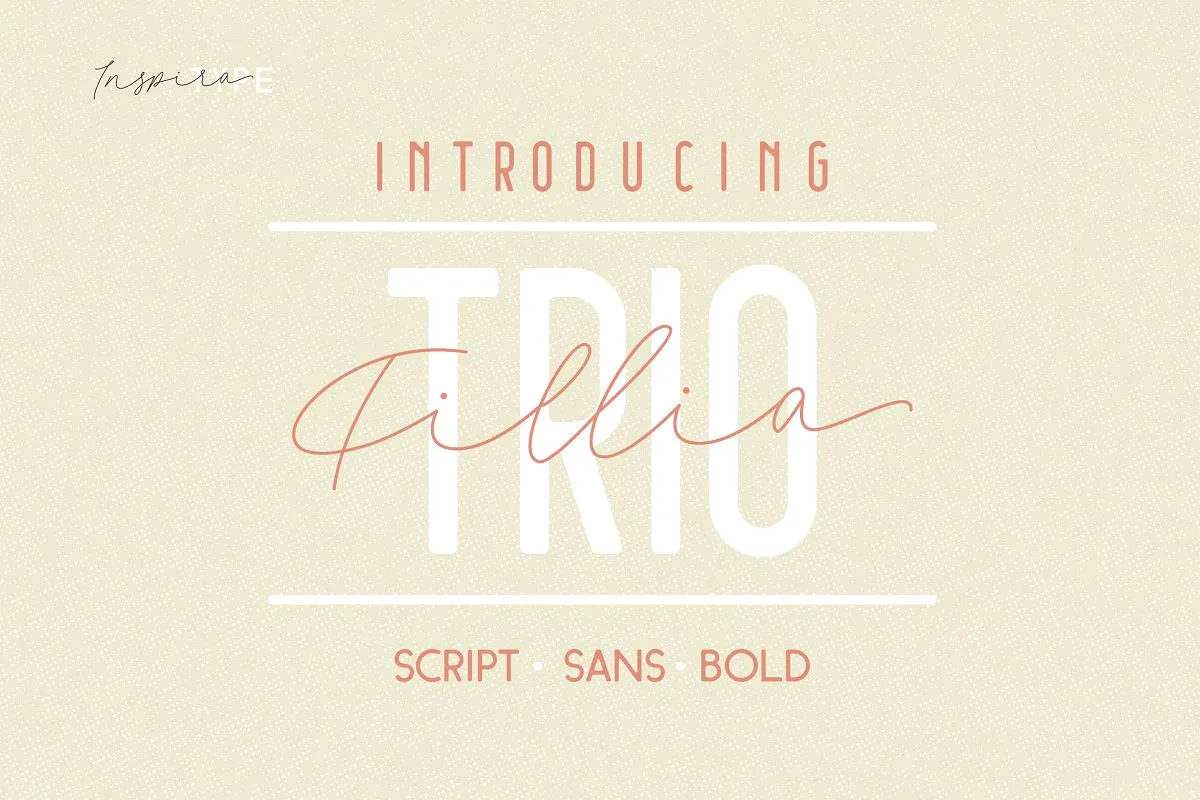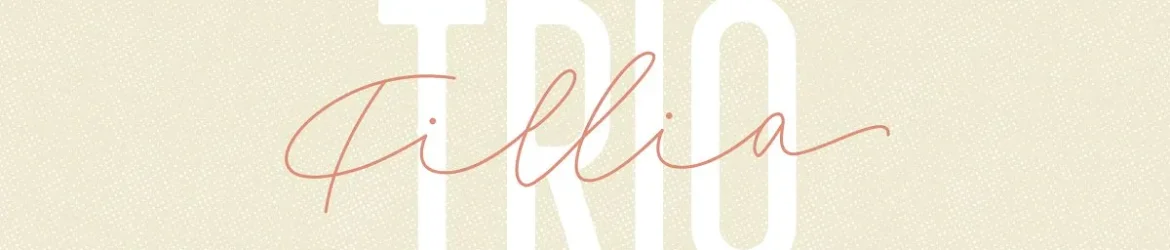
Filia Font Trio – Download Grátis
Através do nosso catálogo de fontes, apresentamos à você a Filia Font Trio, uma trindade inovadora que inclui três estilos distintos: Script, Sans e Bold. Desenvolvida pelo Designer Inspiratype, esta font se destaca por sua influência clássica nas obras gráficas modernas. Através da técnica do desenho à mão livre, Filia traz um estilo único, perfeito para qualquer projeto de identidade visual que você possa imaginar. É ideal tanto para o design de logotipos quanto para letras de carta ou até mesmo a criação de peças impressas como posters e etiquetas. Comumente usada em aplicações de moda, Filia também se destaca por suas alternativas OpenType, ligações comuns e swashes, permitindo-lhe criar designs personalizados. Neste trio de fontes, você encontrará uma ampla gama de variáveis para cada caractere, incluindo números e símbolos. Suas possibilidades são limitadas apenas pela sua imaginação e habilidade no design gráfico. Ideal tanto para profissionais do design quanto para amantes da arte visual, a Filia Font Trio é um atalho fácil para tornar qualquer projeto de design mais interessante e único. Seja você criando uma nova marca ou decorando seu próximo projeto, esta font oferece o nível necessário de flexibilidade para expressar suas ideias com estilo e eficácia.